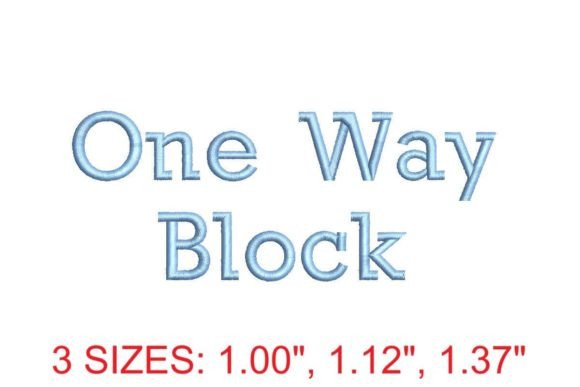
One Way Block Font
Шрифт One Way Block Font — це спеціалізований набір для машинної вишивки з ПЕС-підтримкою, створений виключно для застосування в односторонніх (one-way) блокових вишивальних сценаріях. Він відрізняється чіткою геометрією літер, оптимізованим керуванням ниткою та мінімалістичним, але висококонтрастним дизайном, що забезпечує чудову читабельність навіть при малих розмірах (від 0,3 дюйма). Цей шрифт ідеально підходить для вишивки на текстилі з обмеженою пружністю — наприклад, на фірмових куртках, бейджах або спортивних сорочках, де важлива передбачувана поведінка стібків без перекручування.
Якість збірки та технічні деталі
Для кого найкраще підходить цей продукт?
Цей шрифт особливо корисний для професійних вишивальних сервісів, які працюють з великими партіями однакових замовлень (наприклад, корпоративна уніформа або товари для подій), а також для дизайнерів-вишивальників, які потребують повного контролю над напрямком стібків для досягнення максимального технічного відтворення. Також він ідеальний для початківців, що вивчають основи PES-оптимізації, оскільки не вимагає ручного редагування траєкторій — готовий до використання «з коробки».
Як це порівнюється з конкурентами
На відміну від універсальних шрифтів, таких як Brother Block або Embrilliance Essentials, One Way Block Font не просто «спрощений блок» — він має глибоко інтегровану one-way логіку прошивки, що робить його недоступним для імітації через звичайне перетворення SVG → PES. У порівнянні з платними рішеннями від Wilcom або Pulse, він не надає 3D-ефектів чи складних затінень, але перевершує їх за швидкістю обробки, компактністю файлів (середній .pes — менше 8 KB) і стабільністю на старих або бюджетних машинах.